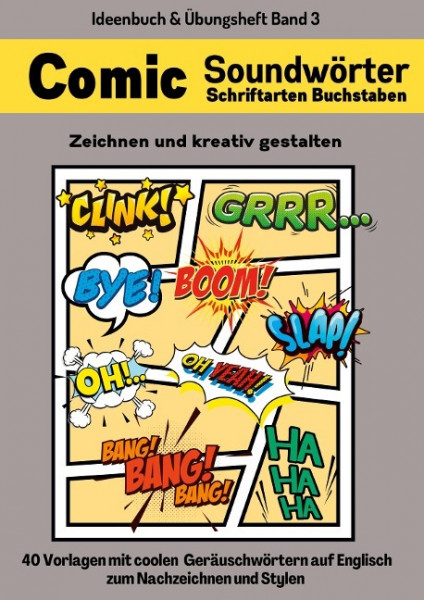
Comic Soundwörter zeichnen und kreativ gestalten Schriftarten Buchstaben Ideenbuch und Übungsheft für Kinder, Teenager, Erwachsene 40 Vorlagen mit coolen Geräuschwörtern auf Englisch
Zur Comic-Erstellung gehört die Darstellung von Sprech- und Denkblasen sowie Soundwörtern (Geräuschwörter). Mit diesem praktischen Übungsbuch wirst du deine Soundwörter-Kenntnisse vertiefen. Hier kannst du gezielt lernen, wie du Soundwörter auf Englisch kreativer stylen kannst. Zum Nachzeichnen stehen 40 coole Soundwörter-Motive auf Englisch - kombiniert mit kreativen Hintergründen und Verzierungen. Produktdetails: + Hochwertiges Heft mit Premium Hochglanz-Cover + Innendesign: Schwarz-Weiß + Stabil gebunden mit dickem Papier (Designs einseitig bedruckt) + Kurze Anleitung + 40 Seiten mit coolen Soundwörtern (1 Design pro Blatt mit viel Platz zum Üben) + Farbtabelle (Lieblingsstifte und Farben besser organisieren) + Viele leere Comic-Seiten, (Paneele) um Entwürfe zu kreieren + Bonusseiten mit Bonus Designs von Navarro, Cake